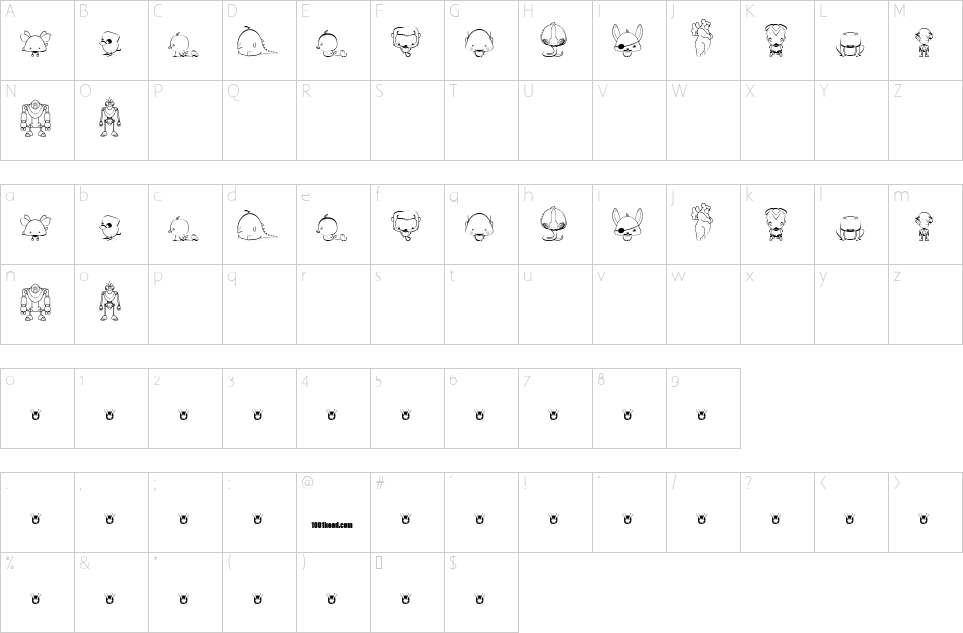
A Mixone Font é uma opção ideal para designers e criativos, oferecendo uma variedade de opções de estilo para personalizar seus projetos de forma única. Desenvolvida pela designer Maelle Keita, esta fonte gratuita está disponível tanto para Windows quanto para Mac. Com um design cuidadosamente pensado, ela ajuda a tornar seus textos mais atraentes e agradáveis para os olhos do usuário. Com seu grande número de downloads (14.124), a Mixone Font prova sua eficácia e popularidade. Se você está procurando por uma opção de fonte grátis e versátil, a Mixone é uma excelente escolha.